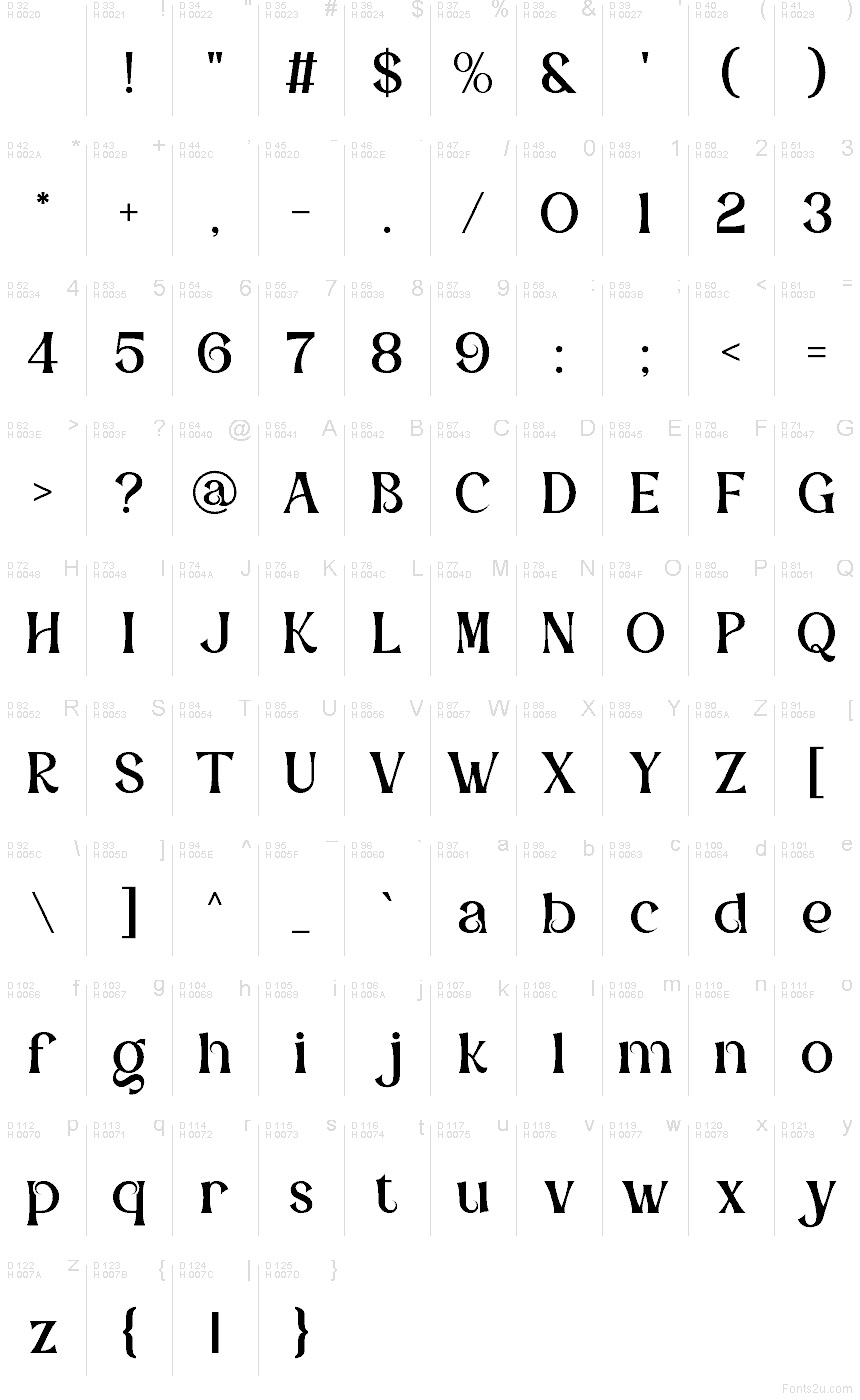
Byena Regular
Byena od ErmediaStudio je bezplatné dekoratívne písmo plné vlnoviek. Tento výrazný font plynie s atramentovými, sochársky pôsobiacimi krivkami, ktoré sú elegantné a zároveň trochu hravé, s odvážnymi ťahmi, ktoré sa rozširujú a zužujú ako písmo kreslené štetcom. Písmená do seba vizuálne zapadajú a vytvárajú hladký, plynulý rytmus, ktorý ťahá zrak cez slovo, vďaka čomu pôsobia aj krátke názvy či nadpisy luxusne a zapamätateľne.
S písmom Byena dodáte svojmu beauty brandingu, logám butikov, obalom, pozvánkam, plagátom a grafike na sociálne siete štýlový, rozprávkový nádych, ktorý je však okamžite čitateľný. Tento bezplatný font žiari najmä pri veľkom zobrazení, kde jeho rozmáchle krivky a veľkorysé tvary môžu voľne dýchať. Pre hlavný text skombinujte Byena s čistým, geometrickým bezpätkovým písmom, aby ste zachovali vyváženosť rozloženia a zároveň nechali jeho dramatické tvary ovládať pozornosť.